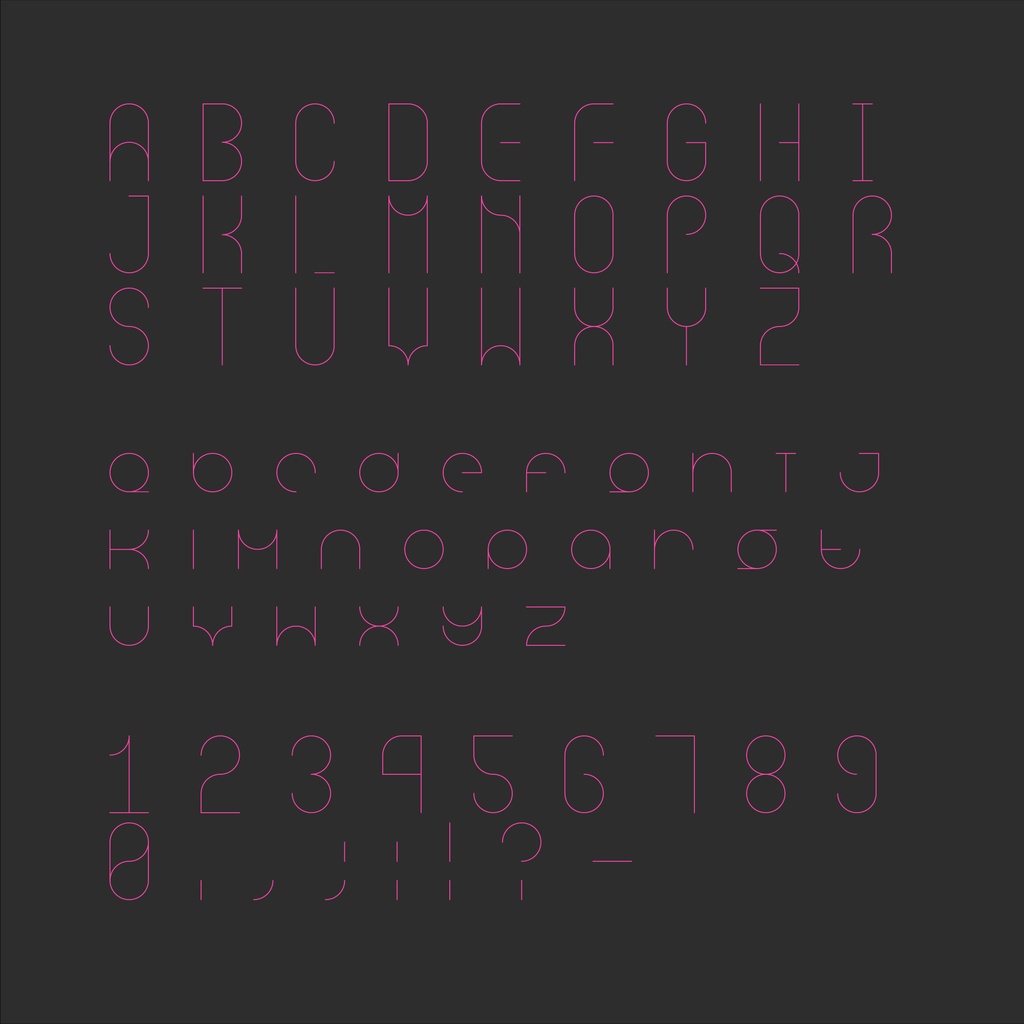
Amari Font 7/100 📢📢📢特記事項📢📢📢 #100日フォントチャレンジ #100日チャレンジ 自分を挑戦した。 100日間て、1日1フォント作る。 デザインは不慣れなため、「すごく下手なデザイン」「他のフォントと似てる」「忙しくて制作できない」などが出てくることがあります。 もしそうなっても許してください!応援よろしくお願いします。 📢デザイン説明 超細字の装飾フォントです。時間があれば、4軸可変フォントにすることも想定している。 📢利用規約 このフォントは無料でダウンロードできる。 個人、商用どちらでも利用可能です。 もしもこのフォントが使用されたら、https://twitter.com/amari_designに教えていただけるとうれしいです! 本素材を使用した作品については、リツイートなどの形で宣伝させていただく場合があります。 フォントのインストール等の技術的なサポートはいたしません。使用して発生したと思われる如何なる問題についても、作者は責任を負わないものとします。 著作権を放棄することはありません。 商標を登録したり、作者であると主張したり、データ自体を販売または再販したりすることは禁じられています。 このコンテンツの最終的な解釈権は作者に帰属します。 内容補充とバージョン更新は製作続けるです。使用する際は最新バージョンにご注意ください。 📢収録內容 ラテン文字、数字だけてを含む70文字が含まれています。 ーーーーーーーーーーーー Twitter:https://twitter.com/amari_design Behance:https://www.behance.net/9f45706b ーーーーーーーーーーーー